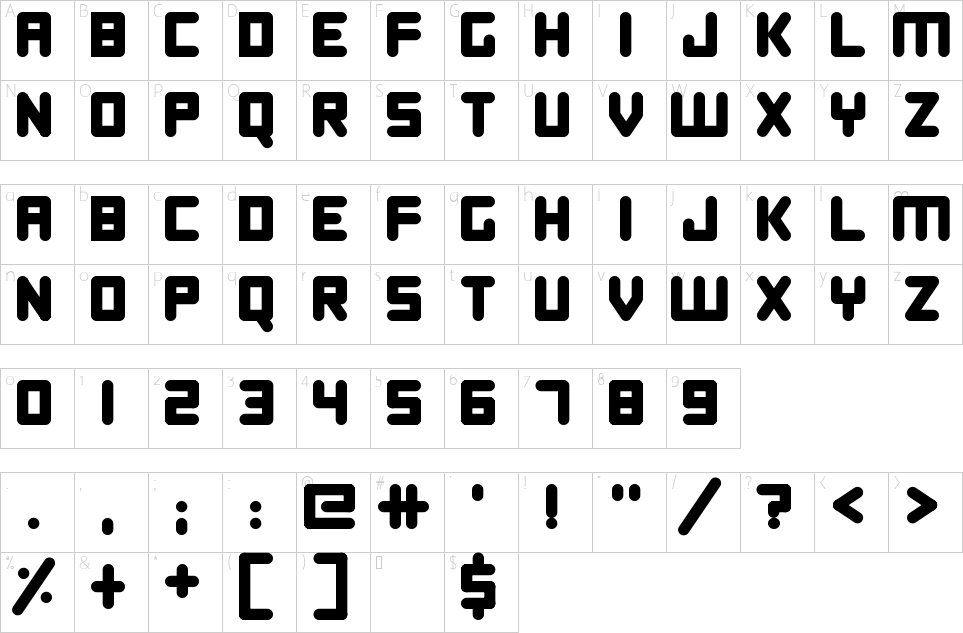
A Digital Dreamers Font é uma elegante escolha para qualquer designer que busca uma fonte moderna e minimalista. Desenvolvida pelo talentoso Darrell Flood, esta fonte é perfeita para aqueles buscando um toque único no design de suas criações digitais. Com seu estilo clean e moderno, a Digital Dreamers Font oferece um visual limpo que pode ser facilmente integrado em projetos de marca, sites ou qualquer outro tipo de arte digital. Sua simplicidade não só ajuda a destacar o texto em seu projeto, mas também adiciona uma leveza ao design, tornando-a uma fonte excelente para trabalhos que buscam um equilíbrio perfeito entre funcionalidade e elegância. E para aqueles que estão sempre à procura de novas opções de fontes, a Digital Dreamers está disponível gratuitamente em seus sistemas Windows e Mac.